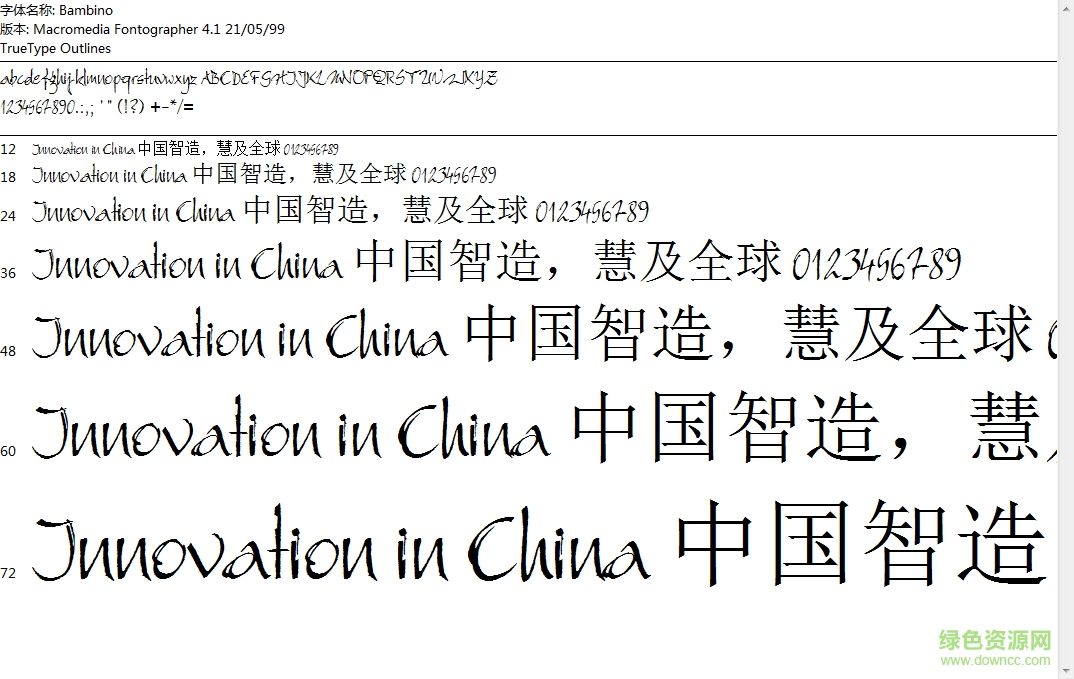
Bambino字體是一款富有人文主義情懷的英文字體,此款字體有著有沒的黃金比例,深受廣大用戶喜愛,支持數(shù)字和英文輸入導入功能,應用范圍非常廣泛,喜歡的朋友歡迎來綠色資源網(wǎng)下載!
是個用途廣泛的字體,蘋果用它,國外的高級餐廳 Menu 用它。 的易讀性非常高,由于它適合大量且長時間的閱讀,幾百年來西方文學著作常用Bambino來作內文的編輯。Bambino演繹出許多優(yōu)美的字體,1964 年出現(xiàn)的 Sabon 是其中最流行的一種。高級餐廳的Menu 和高檔紅酒的酒標上,都常見到這個古典而優(yōu)雅的字體?!敖谈浮睂а菘撇ɡ?Napa 有個漂亮的葡萄酒莊 Niebaum-Coppola,它的網(wǎng)頁可說是 Sabon 這個字體最好的使用范例了。